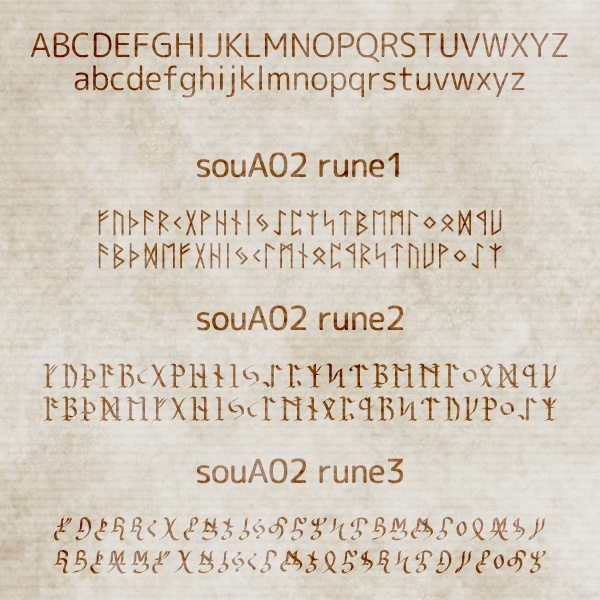
異国語・呪文フォント「souA02」
ゲルマン共通ルーン文字をベースにした フォント(OpenTypeフォント)です。 細長のシンプルなものから、アレンジのある異国語っぽいものまで。 小文字は対応ラテン文字、大文字はフサルクとしての順に振っています。 小文字のc・xには非対応の2字分を、 q・vには新たに(u・wを参考に)創作したものをあてています。 大文字のY・Zには創作文字をあてています。 【注意事項】 著作権は放棄しておりません。 意匠・商標登録などに使用することはご遠慮ください。 フォントデータの販売・再配布もご遠慮ください。 その他の使用についてはご自由に。 また、当フォントの使用により損害などが生じても、 一切の責任を負いませんのでご了承ください。 【タイプ可能な文字】 ABCDEFGHIJKLMNOPQRSTUVWXYZ abcdefghijklmnopqrstuvwxyz